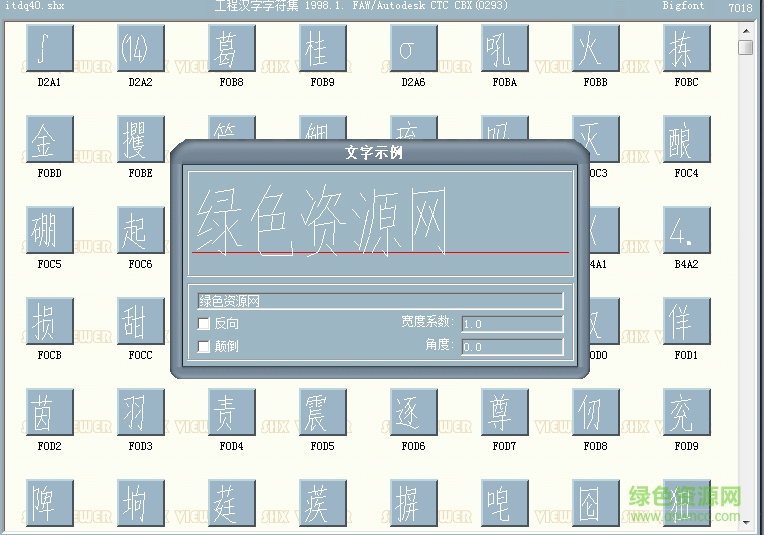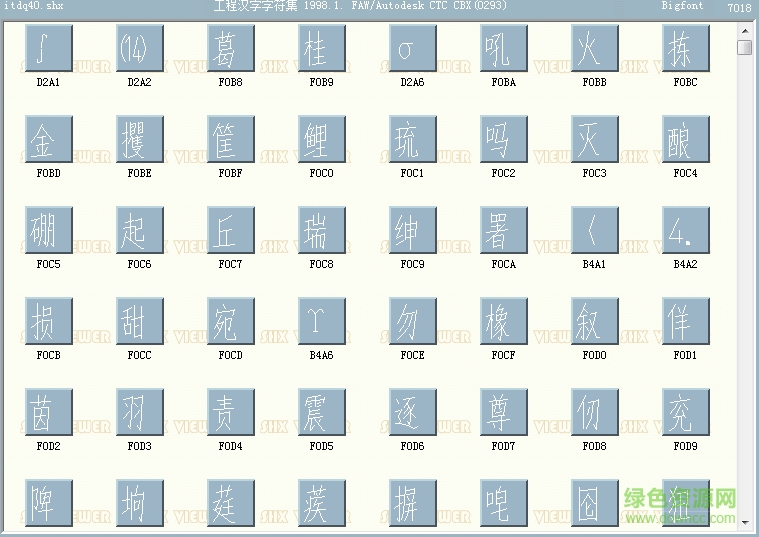
itdq40.shx字體是autocad軟件中常見的一款字體,包含了各種標(biāo)點(diǎn)符號和中文字體,字形端正結(jié)構(gòu)嚴(yán)謹(jǐn),應(yīng)用效果出色,對于建筑專業(yè)設(shè)計(jì)人員很有幫助,需要這款字體的朋友快來綠色資源網(wǎng)下載吧!
cad里所稱的shx字體和大字體(也叫bigfont),都是autocad專用專有的字體。大字體也是shx字體,是shx字體的一種特殊形式。最初的shx字體支持的是ANSI字符,后來擴(kuò)大到支持非ANSI字符,也就是大字體或bigfont,用雙字節(jié)儲存,這也就是為什么叫大字體的原因。